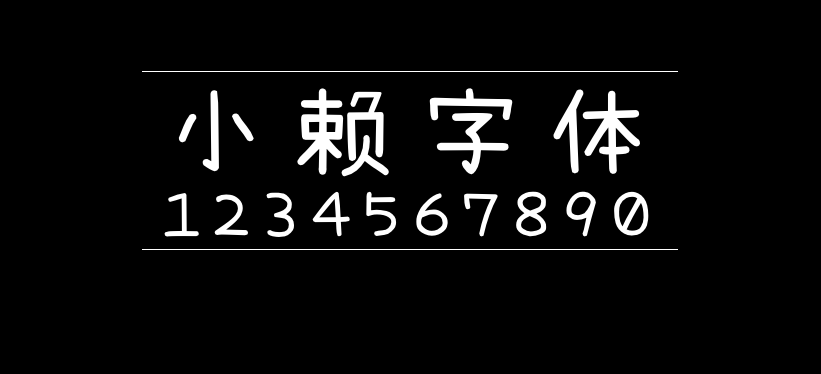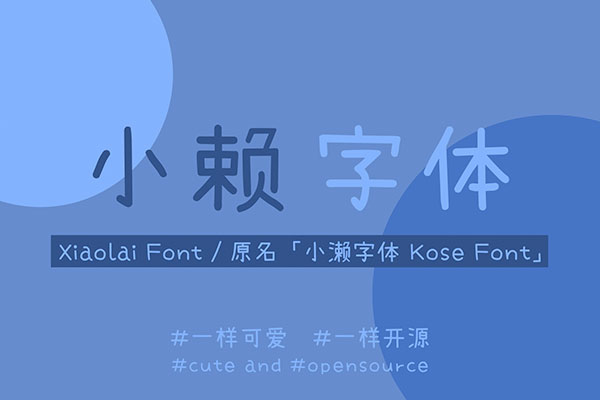
小赖字体
濑户字体是由日本的业余字体设计师瀬戸のぞみ制作,支持JIS第一至第四级,支持繁体和简体中文(部分)。目前最新的版本是2014年9月24日的6.20版本,原作者已经很久不更新了。后来Max在原来的濑户字体基础上,推出了内海字体,补齐了台湾教育部门列出的4808个常用字,并增加了闽南语、粤语常用字,弥补了繁体中文地区常用字缺字缺憾。
但是,这款可爱的开源字体,仍然缺少一部分简体字,这对于大陆的用户来说,可能会造成一些不便。所以,国内设计师落霞孤鹜开始了这个项目,旨在补足濑户字体和内海字体缺少的简体字。落霞孤鹜利用业余时间将濑户/内海字体原有的部件进行拼接和调整,为内海字体补全简体中文汉字。目前已经制作了1083 个字符,与内海字体搭配可以显示GB2312范围内的所有汉字。
后来国内网友发现“落霞孤鹜”的版本在竖排的时候会出现文字粘连的问题,于是对字体进行了修正。 本次主要修正了以下问题:
1、把字体的名称由“内海フォント-Regular 简体补全”修改成“小濑字体”,英文名称为xiaolai SC。
2、汉字字体宽度由2024调整为较为常用的1000。
3、精简大量用不上的其他国家的字符,主要保留英文字母、汉字、假名和一些其他字符。
本字体项目原名为 「小濑字体」 ,后来由于很多人都把「濑」打成「赖」,索性把「氵」去掉,改名 「小赖字体」 。
本字体是 濑户字体 / 内海字体 的简体中文化改良,利用濑户/内海字体里原有的部件,对原字体中缺少的汉字进行补足,主要为 GB2312 及《通用规范汉字表》里的汉字,其余的汉字、谚文、特殊符号用 cjkFonts 全濑体 补全。现有 CJK 基本区汉字 20949 个,扩展 A 区汉字 6582 个,B 区汉字 368 个,C 区汉字 44 个,D 区汉字 9 个,E 区汉字 108 个,F 区汉字 1 个(「韡」的简体字「?(U+2E9F5)」),G 区汉字 2 个(biáng 字的简繁体「?」(U+30EDD)「?」(U+30EDE))。
该字体可显示 GB18030-2000 范围内的全部汉字(共 27484 个),以及《通用规范汉字表》里的全部汉字(共 8105 个),满足中国大陆用户的使用需要。此外可显示日文假名、谚文 (韩文、朝鲜文) 音节和思源黑体可以显示的特殊符号,可直接用作手机字体。